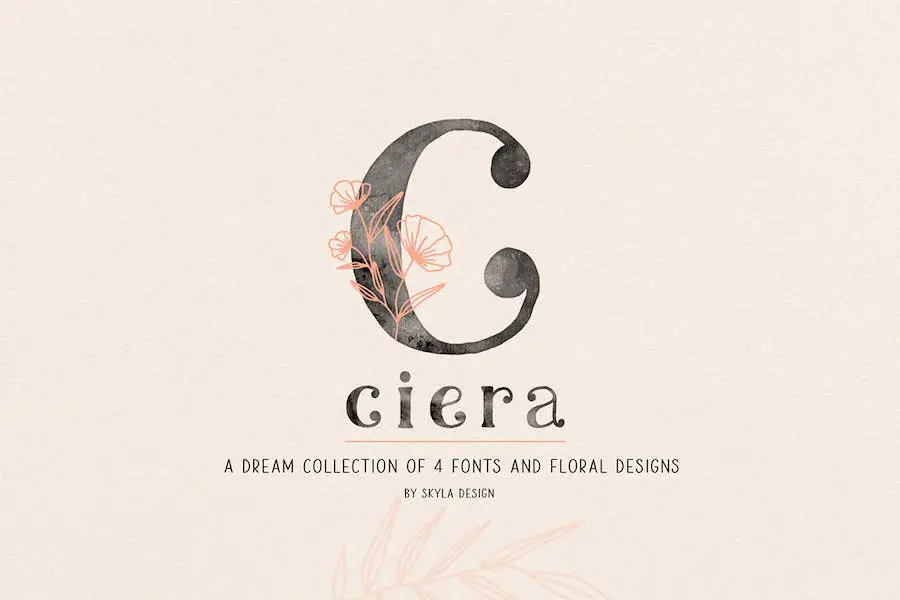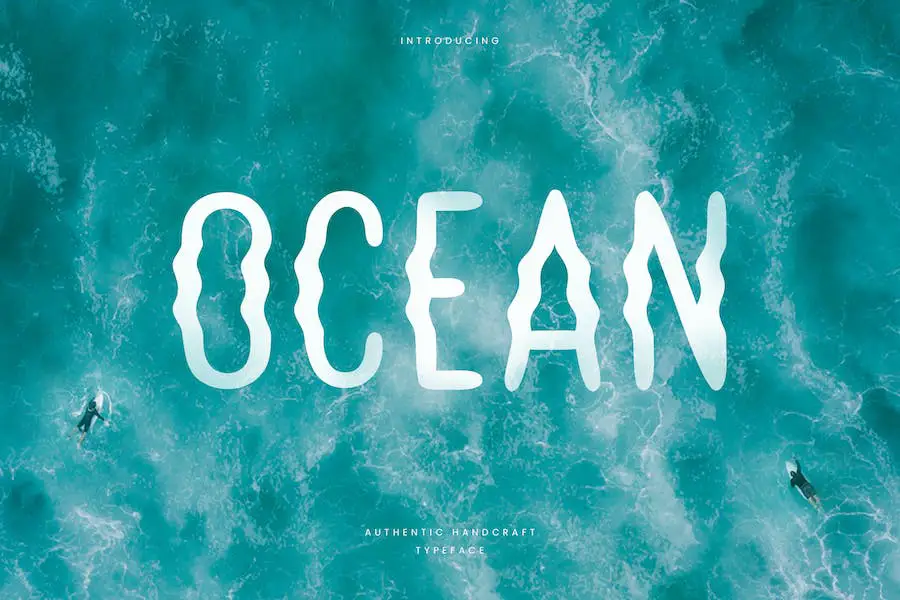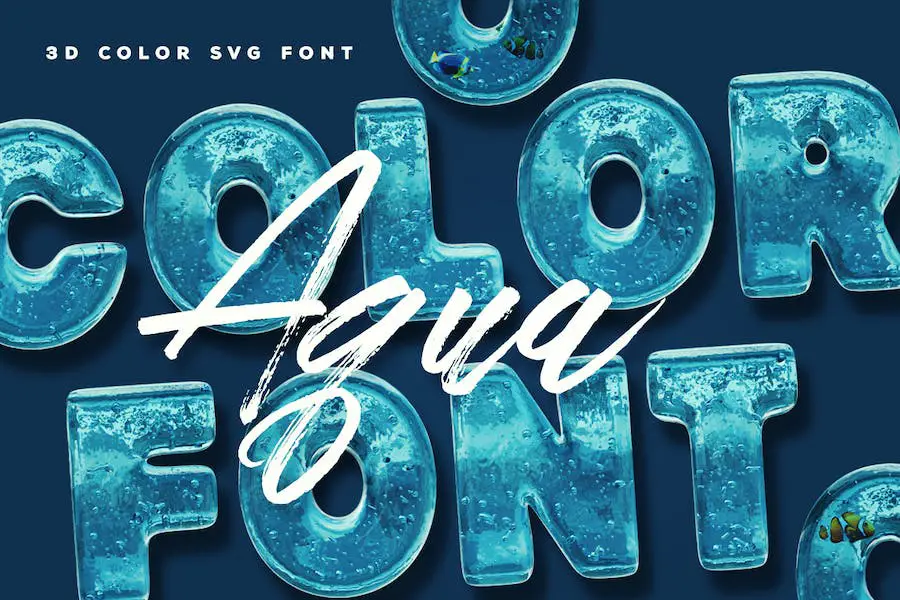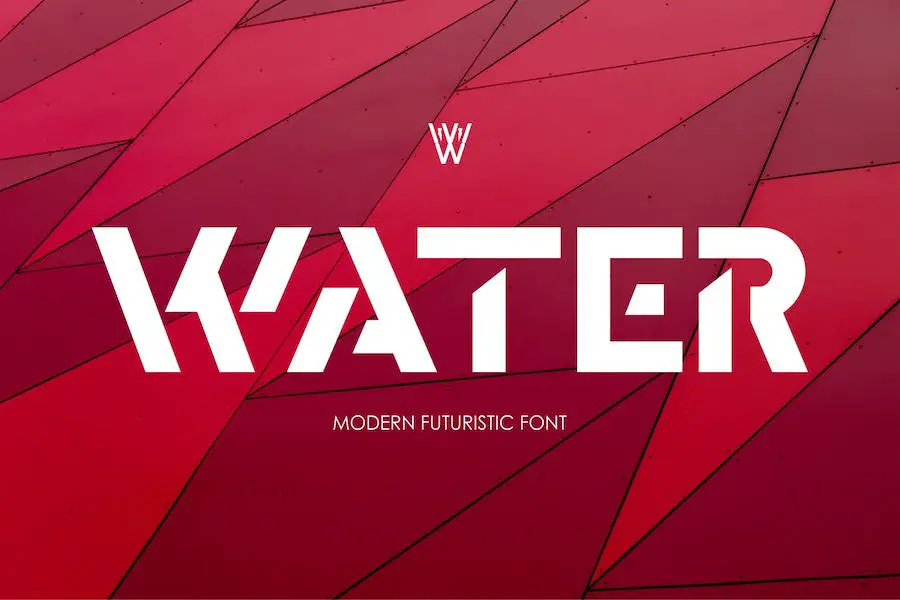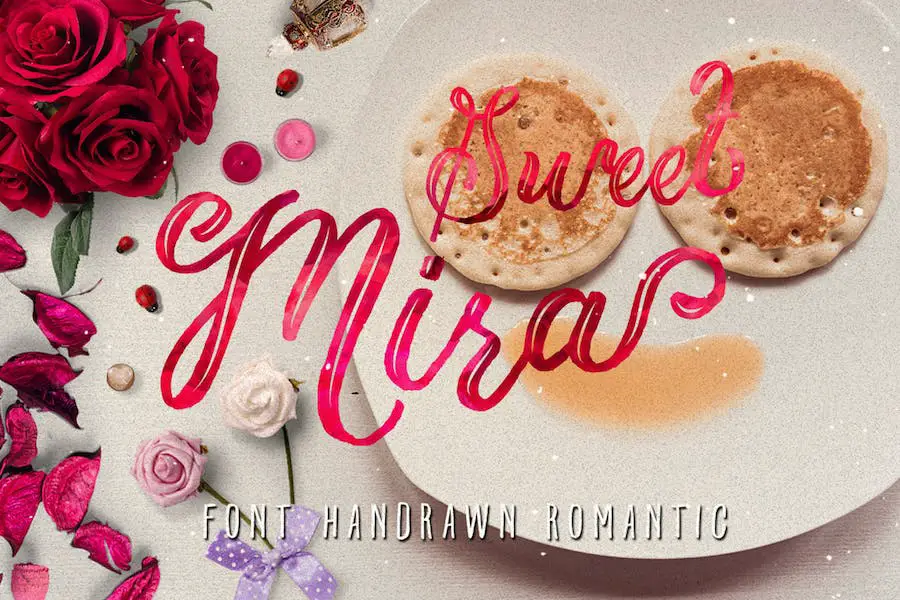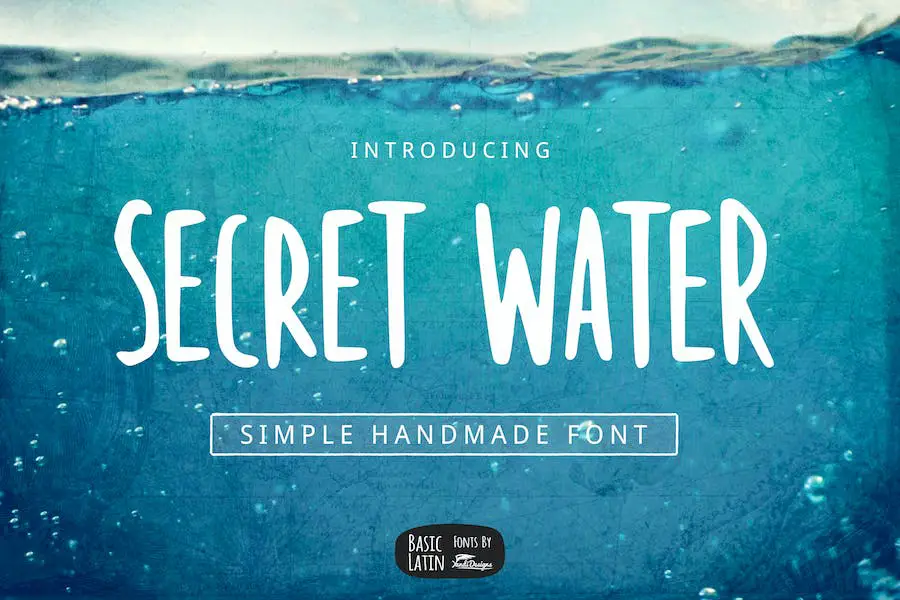
Yayınlanan: 2023-08-03Projelerinizi yükseltmek için mükemmel yazı tipini arayan bir grafik tasarımcı mısınız? Başka yerde arama! Bu blog yazısında, tasarımlarınızı bir sonraki seviyeye taşıyacak en iyi 25 su temalı yazı tipini derledik.
İster bir logo, ister bir web sitesi veya başka bir görsel proje üzerinde çalışıyor olun, bu yazı tipleri kesinlikle bir sıçrama yapacaktır.
Şimdi, su yazı tiplerinin neden keşfedilmeye değer olduğunu merak ediyor olabilirsiniz. Profesyonel grafik tasarımcıları arasında yapılan bir ankete göre, %85'i sudan ilham alan yazı tiplerini kullanmanın genel tasarım estetiğini önemli ölçüde artırabileceğine inanıyor.
Akışkanlığı, huzuru ve çok yönlülüğü simgeleyen güçlü bir unsur olan su, onu modadan markalaşmaya kadar çeşitli sektörlerde popüler bir seçim haline getiriyor.
Öyleyse, hemen dalış yapalım ve mevcut en iyi 25 su yazı tipini keşfedelim. Bir gölün yumuşak dalgalarını taklit eden zarif ve akıcı yazılardan, okyanusun çarpan dalgalarını yakalayan cesur ve dinamik sans seriflere kadar, yaratıcı vizyonunuza uyacak çok çeşitli seçenekler bulacaksınız.
Tasarımlarınızı suyun güzelliği ve sembolizmi ile geliştirerek, hedef kitlenizde gerçekten yankı uyandıran görsel bir deneyim yaratın.
En İyi Premium Su Yazı Tipleri
Grafik tasarım projelerinize yaratıcı bir hava katmak mı istiyorsunuz? En İyi 25 Su Yazı Tipi seçimimizden başka yere bakmayın! Bu birinci sınıf yazı tiplerinin tasarımlarınızı yükselteceğinden ve onlara ekstra bir stil dokunuşu vereceğinden emin olabilirsiniz.
Bu harika seçenekleri keşfetme fırsatını kaçırmayın – aşağıdaki makalede bunlara göz atın!
Yaz Sıçraması
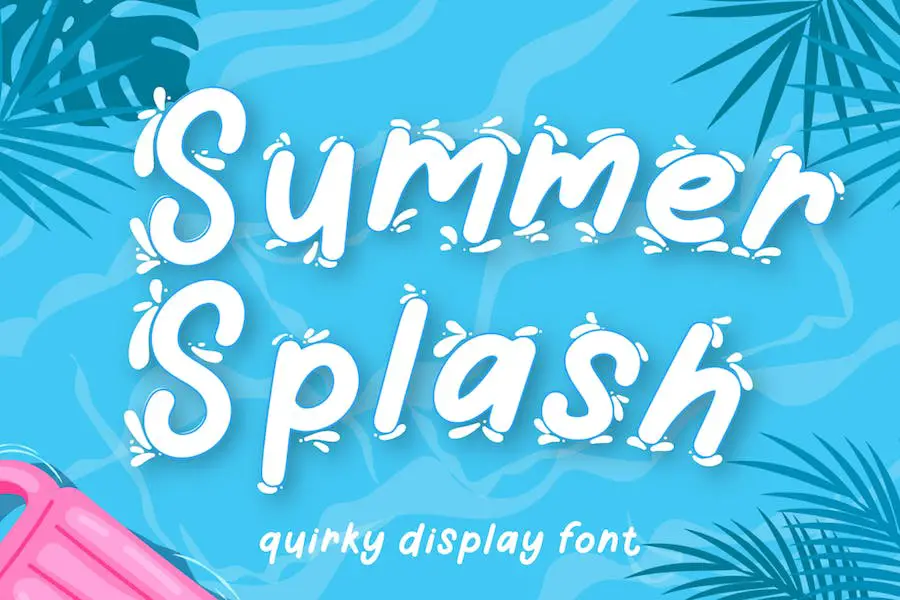
Summer Splash, sıçrayan suyun özünü yakalayan benzersiz bir ekran yazı tipidir. Bu yazı tipinin iki stili vardır: normal ve görüntülü, grafik tasarımcılara projelerini canlandırıcı sudan ilham alan bir tasarım dokunuşuyla geliştirmeleri için yaratıcı özgürlük verir.
Sudan ilham alan bu yazı tipi, herhangi bir grafik tasarım projesine canlandırıcı ve eğlenceli bir dokunuş getiriyor. Eşsiz stili, su sıçramalarının hareketini ve akışkanlığını taklit ederek tasarımlarınıza dinamik bir unsur ekler.
Summer Splash'ın normal yazı tipi seçeneği, başlıklar, başlıklar veya öne çıkması gereken herhangi bir metin oluşturmak için mükemmel olan temiz ve zarif bir görünüm sunar. Pürüzsüz kıvrımları ve kenarları, tasarımlarınıza parlak ve profesyonel bir görünüm kazandırır.
Paltrow
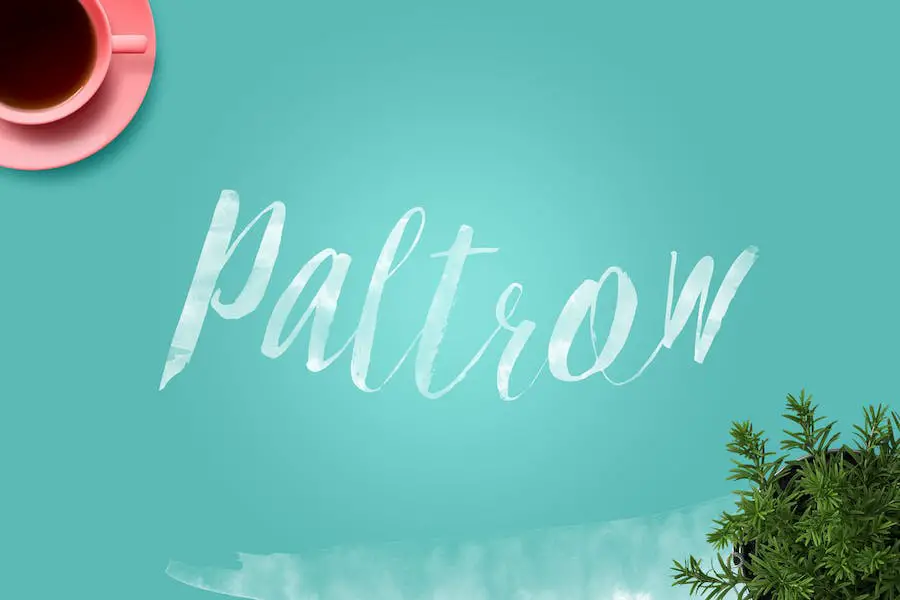
Paltrow, mürekkep veya suluboya tabanlı tasarımlarda kullanılmak üzere özel olarak tasarlanmış, elle boyanmış benzersiz ve sanatsal bir yazı tipidir. Cesur ve etkileyici fırça darbeleriyle bu yazı tipi, herhangi bir projeye özgünlük ve yaratıcılık katar.
İster bir davetiye kartı, ister bir başlık veya bir poster üzerinde çalışıyor olun, Paltrow, tasarımınızı ön plana çıkarmak için mükemmel bir seçimdir.
Elle fırçalanmış yazısı, onu çeşitli uygulamalar için çok yönlü hale getiren bir zarafet ve stil duygusu getiriyor. Bu çarpıcı suluboya yazı tipiyle yaratıcılığınızın akmasına izin verin.
Aynı şekilde
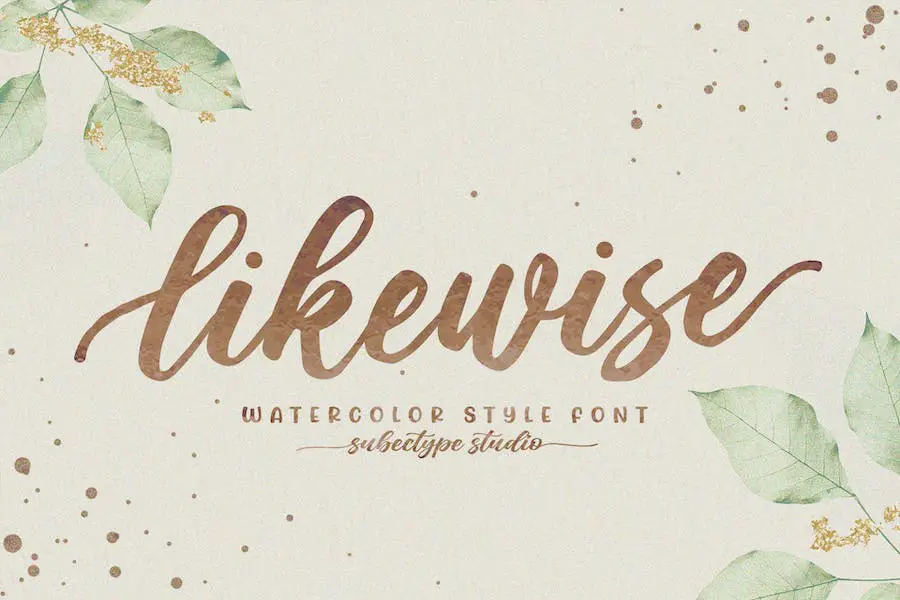
Aynı şekilde eğlence, çekicilik ve özgünlük yayan bir sulu boya yazı tipidir. Bu neşeli ekran yazı tipi, çocukların etkinlikleri ve okul projeleri için mükemmeldir ve her türlü tasarıma eğlenceli bir dokunuş katar.
Eşsiz stili, suluboyaların özünü yakalar ve projelerini yükseltmek için bir yazı tipi arayan grafik tasarımcılar için mükemmel bir seçimdir.
Aynı şekilde, tasarımlarınıza kaprisli ve neşeli bir havayı zahmetsizce dahil edebilir, onların öne çıkmasını ve daha genç bir kitleye hitap etmesini sağlayabilirsiniz.
Bu keyifli su yazı tipi, karakter ve kişiliğe sahiptir. El yazısı tarzı, tasarımlarınızda bir sıcaklık ve samimiyet duygusu yaratarak bir özgünlük dokunuşu katar.
İster posterler, ister davetiyeler veya eğitim materyalleri tasarlıyor olun, aynı şekilde izleyicilerinizi kesinlikle cezbedecek eğlenceli ve canlı bir enerji getirir. Bu, tuvalinize suluboya sıçraması gibi, tasarımlarınıza sanatsal bir hava katıyor.
Su altı
Underwater Font, macera ve keşfin özünü yakalayan cesur ve büyüleyici bir yazı tipidir. Bu benzersiz yazı tipi, projelerine biraz heyecan katmak isteyen grafik tasarımcılar için idealdir.
Sıvı sudan ilham alan tasarımıyla Underwater Font, bilinmeyen derinliklere dalmanın ve dünya çapında bir yolculuğa çıkmanın heyecanını akla getiriyor. Girift detayları ve akıcı hatları, merak ve keşif duygusu uyandırmayı amaçlayan projeler için mükemmel bir seçimdir.
İster bir seyahat broşürü, ister bir açık hava şirketi için bir logo veya heyecan verici bir etkinlik için bir poster tasarlıyor olun, Underwater Font tasarımınızı anında yükseltecek ve izleyicilerinizi büyüleyecek. Underwater Font dünyasına dalın ve yaratıcılığınızın okyanusun derinlikleri gibi akmasına izin verin.
Su Galonu
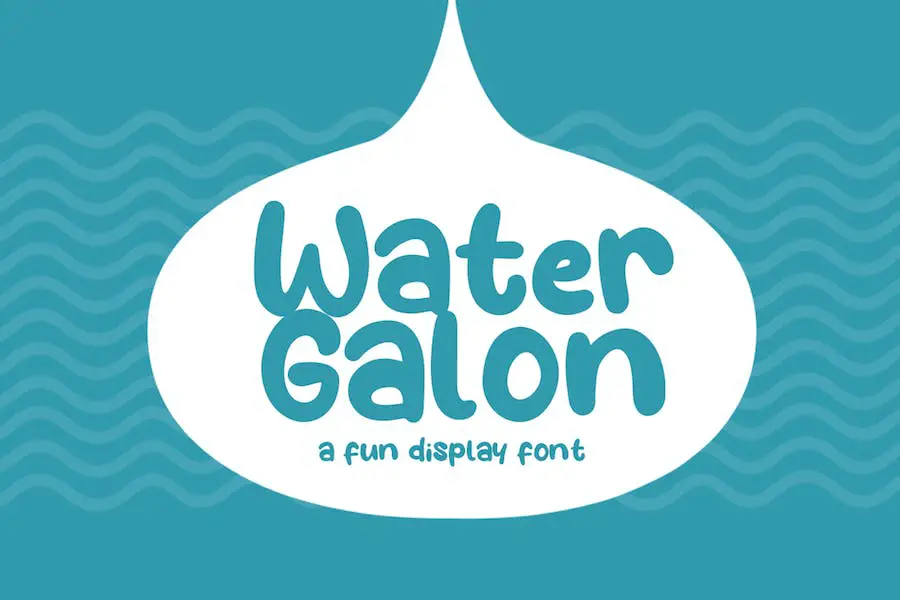
Water Galon eğlenceli bir ekran yazı tipidir. Bu neşeli yazı tipi, tasarım projelerinize eğlenceli bir dokunuş eklemek için mükemmeldir. İster bir logo, marka, tebrik kartı veya poster üzerinde çalışıyor olun, Bubble Water kreasyonlarınıza canlı ve enerjik bir hava katacaktır.